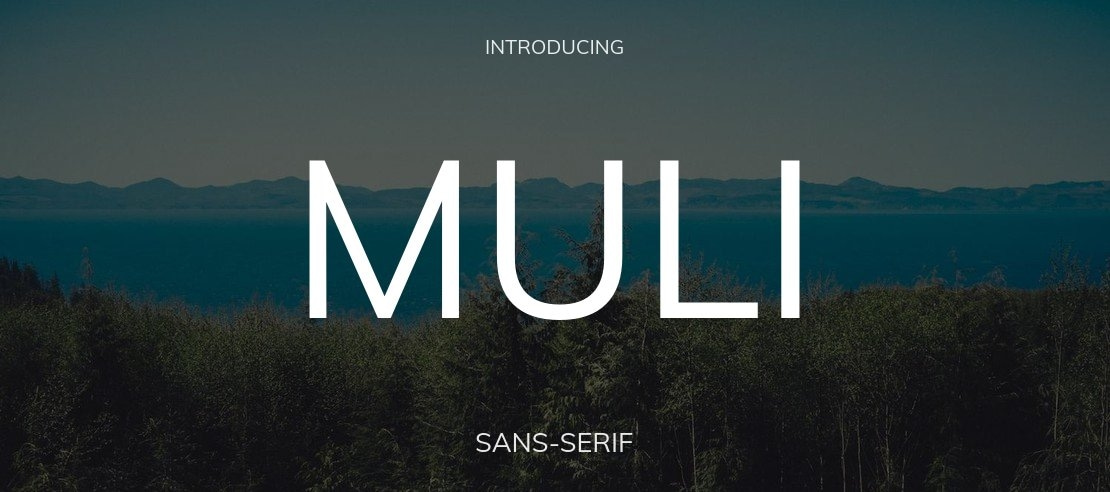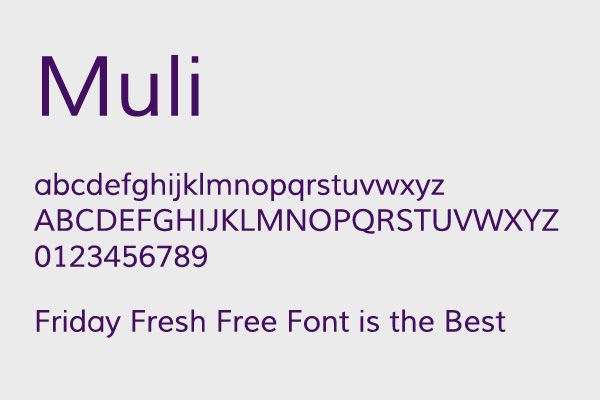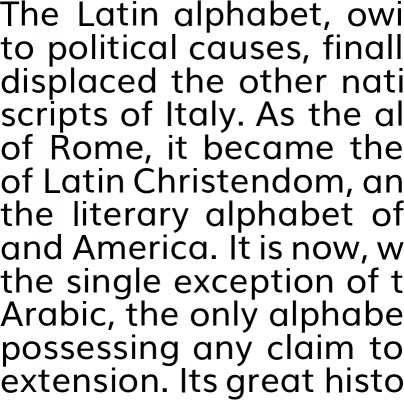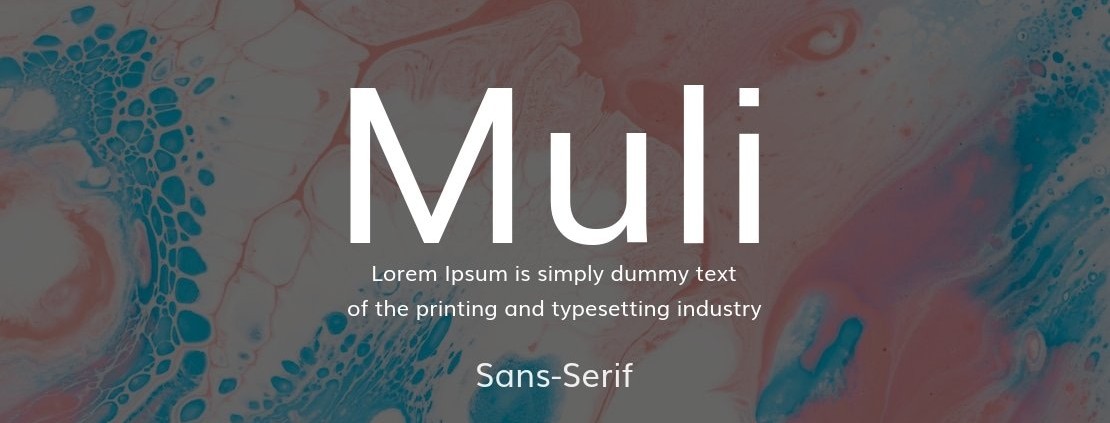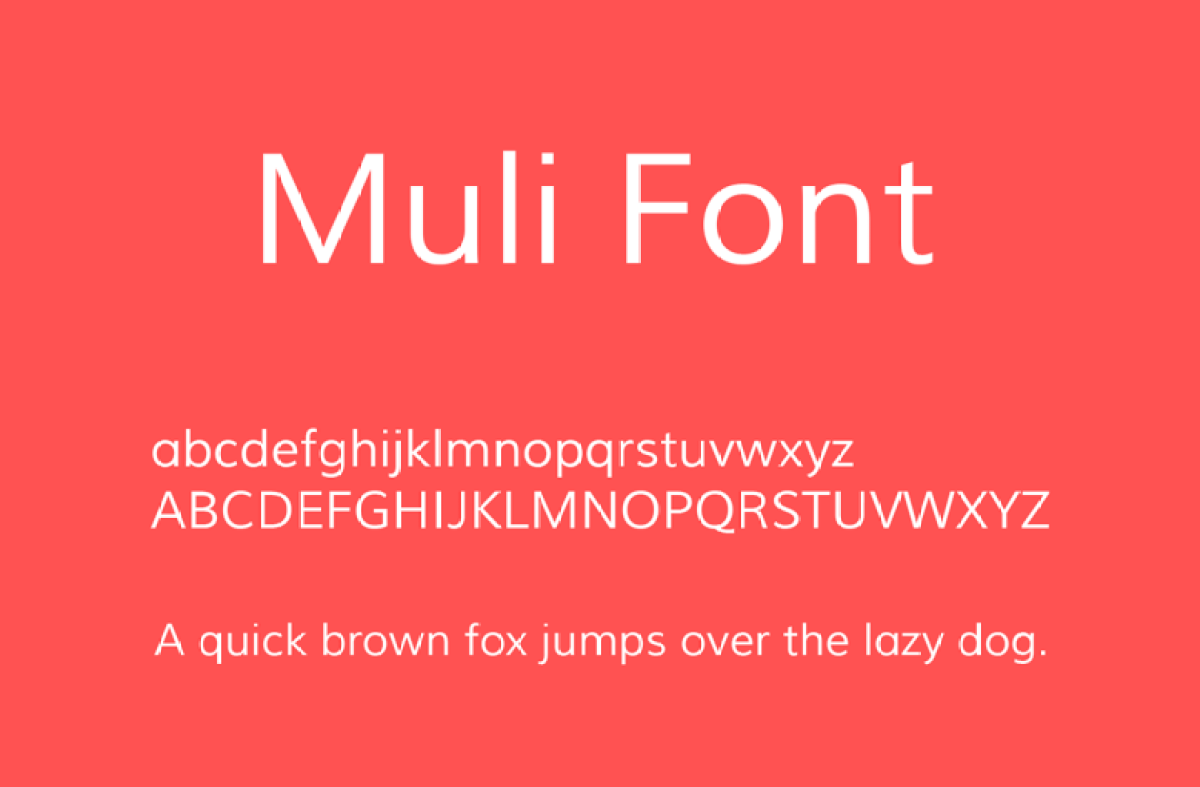
Font Muli là gì?
Muli là một bộ phông chữ thuộc dòng Sans-serif tối giản vô cùng nổi tiếng, ban đầu được thiết kế bởi Vernon Adams. Đặc trưng của Muli là cấu trúc hình học cân đối, các đường nét thanh mảnh nhưng vô cùng vững chãi, mang lại cảm giác minh bạch, hiện đại và rất “Tây”. Đây là sự lựa chọn phổ biến cho các thiết kế nhận diện thương hiệu công nghệ, giao diện website (UI/UX) và bao bì sản phẩm theo phong cách Minimalism.
Điểm mạnh vượt trội của font Muli chính là khả năng hiển thị cực kỳ rõ nét ở mọi kích thước, từ những dòng thông tin nhỏ trên tem nhãn đến các tiêu đề lớn trên bạt quảng cáo. Bản tải font Việt hóa Muli tại In Viva đã được xử lý kỹ lưỡng từng dấu thanh tiếng Việt, đảm bảo Kerning (khoảng cách giữa các chữ) luôn hài hòa và không bị lỗi chân chữ khi gõ văn bản dài. Sử dụng phông chữ này giúp các ấn phẩm cho doanh nghiệp của bạn toát lên vẻ ngoài sang trọng và chuyên nghiệp cao.
Lưu ý: Bộ font Muli có rất nhiều biến thể độ dày. Khi thiết kế in ấn trên nền tối, bạn nên chọn biến thể Regular hoặc SemiBold để chữ không bị mờ nhạt sau khi cán màng.
Ứng dụng font Muli Việt hóa trong thiết kế và in ấn
Vẻ đẹp hiện đại của Muli giúp nâng tầm giá trị cho mọi ấn phẩm truyền thông và ấn phẩm của doanh nghiệp:
- Sản xuất bao bì hộp yến sào và mỹ phẩm: Sử dụng font Muli cho các đoạn văn bản hướng dẫn sử dụng mang lại cảm giác sạch sẽ, tin cậy. Khi in trên hộp giấy Ivory cán màng mờ, phông chữ này tạo nên hiệu ứng thị giác vô cùng tinh tế và cao cấp.
- Thiết kế bộ nhận diện văn phòng đồng bộ: Từ danh thiếp, phong bì thư đến túi giấy đựng tài liệu, Muli giúp thương hiệu của bạn trông như một doanh nghiệp toàn cầu chuyên nghiệp. Sự tối giản của font chữ này giúp khách hàng tập trung tối đa vào thông tin cốt lõi.
- In ấn sản phẩm công nghệ in logo: Logo doanh nghiệp dùng phông Muli khắc laser trên sạc dự phòng hoặc in UV trên bình giữ nhiệt kim loại tạo vẻ ngoài hiện đại, bền bỉ và không bao giờ lỗi mốt theo thời gian.
- Xây dựng Catalogue và hồ sơ năng lực: Việc sử dụng font Muli với các độ dày khác nhau (Hierarchy) giúp ấn phẩm có bố cục chặt chẽ, dễ đọc, phù hợp để trình bày các dự án quy mô lớn cho đối tác.
- Trang trí voucher và thẻ VIP tri ân: Tạo sự khác biệt thông qua những dòng chữ thanh lịch, hiện đại trên chất liệu giấy mỹ thuật cao cấp có vân.
Sử dụng font chữ Muli cần lưu ý gì?
Để bản in sử dụng font Muli đạt độ sắc sảo và thu hút, designer cần quan tâm các yếu tố kỹ thuật sau:
- Lựa chọn độ dày nét phù hợp vật liệu: Khi in trên giấy Kraft có độ thấm mực cao, bạn nên tránh dùng biến thể Light (nét mảnh). Hãy dùng nét Regular hoặc Medium để đảm bảo chữ không bị “nuốt” mất khi mực khô.
- Kiểm soát hệ màu CMYK: Đảm bảo màu sắc chữ Muli sau khi in đúng với mã nhận diện thương hiệu, đặc biệt là khi thực hiện kỹ thuật phủ UV định hình lên bề mặt chữ để tạo độ bóng nổi.